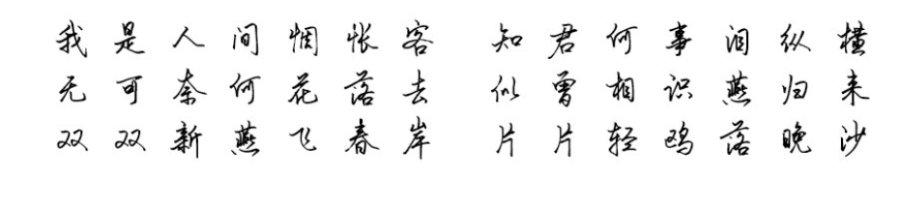
一款兼具实用性与艺术性的字体-安景臣手写体行书字帖版
安景臣手写体行书字帖版字体是为了规范硬笔行书书写,推广普及行书字体而编写制作的一款兼具实用性与艺术性的字体。广泛应用于:字帖出版、内部教程、速成规范,广告语设计、影视字幕、印刷排版等领域,是不可多得的行书规范字体。编写制作者安景臣的第一款字体即是钢笔行书字体,以行书见长,此款字体是目前最满意的作品,且拥有独立版权,编写与制作均由个人独立完成,在字库行业极为罕见!值得下载、应用及收藏!目前这款商用字体已经在字体视界上线,喜欢的这款字体可前往官网搜索字体名称下载。
字样展示:安景臣手写体行书字帖版